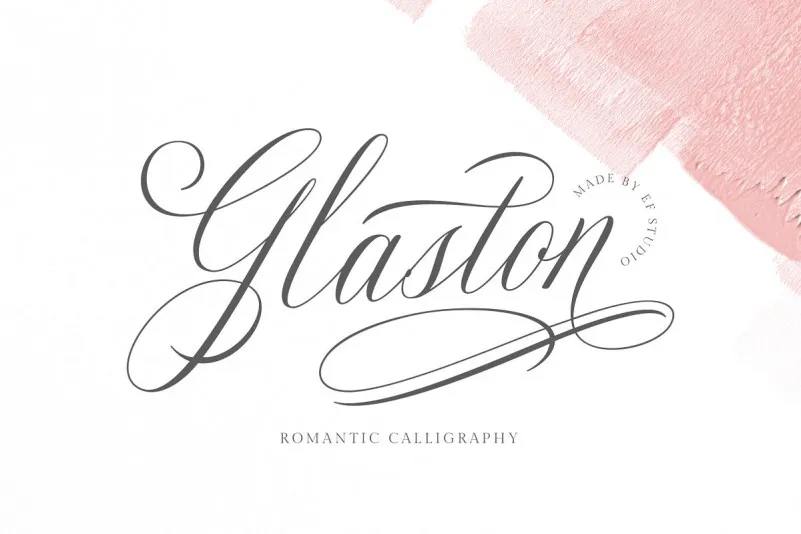
Aqui está uma versão descritiva para a página de download da fonte ‘Glaston Calligraphy Font’, seguindo as orientações fornecidas: Gratidão pela atenção! Este é um novo tipo romântico de caligrafia. É outro belo tipo de caligrafia moderna, que junta o estilo das caligrafias clássicas com o moderno. Introduzimos a fonte Glaston. Foi projetada e compartilhada pela Ef Studio. A fonte Glaston é perfeita para rótulos de vinho tinto, batas de vodka, embalagens luxuosas, papelaria de casamento, convites, cartões de negócios, marca e outros projetos que exigem um toque de escrita a mão e luxo. Esta fonte é uma excelente escolha para criar designs elaborados com um ar autêntico e sofisticado.